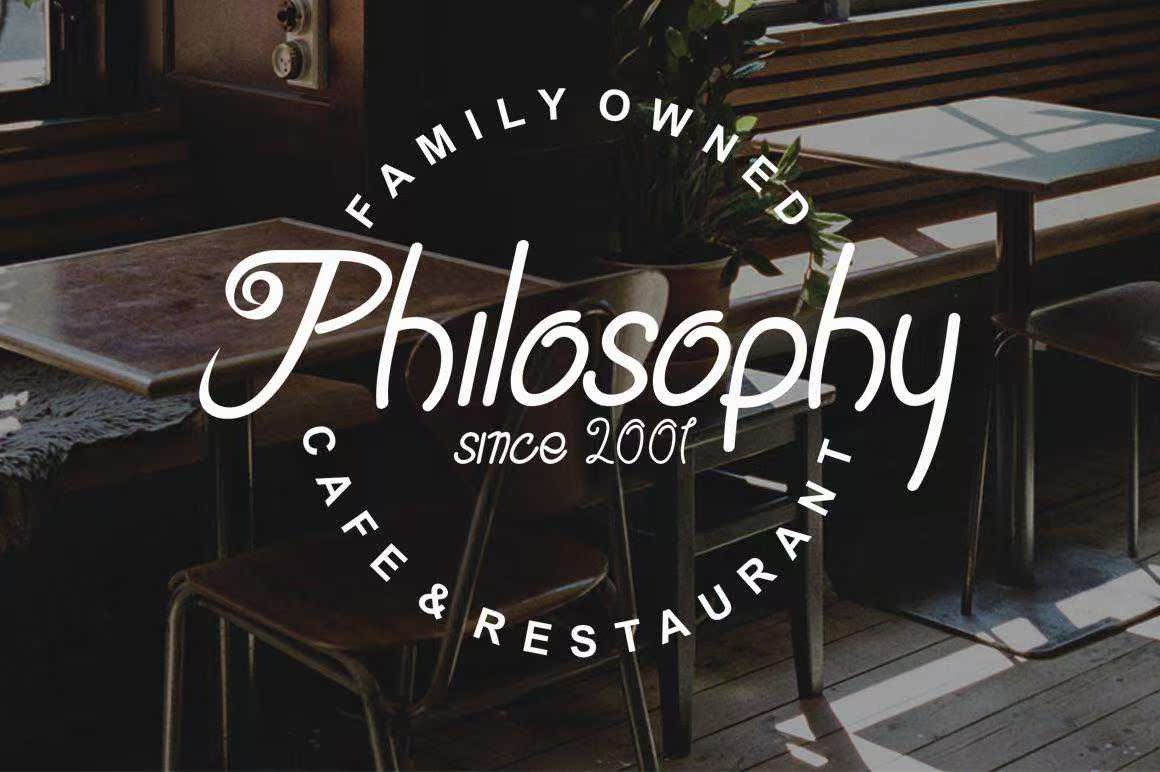
可用于Salogo或商标/品牌的字体。从该概念出发,我将“Serasa”命名为“Serasa”,并将字体书写为“alittle”。大多数字体为Orogasarelatin,斜体,手写在ConnectSeachletter上,我希望对可用于Salogo或商标/品牌的字体进行区分。从该概念出发,我将“Serasa”命名为“Serasa”,并将字体书写为“alittle”。大多数字体为Orogasarelatin,斜体,在ConnectSeachletter上手写,我想做一个区分